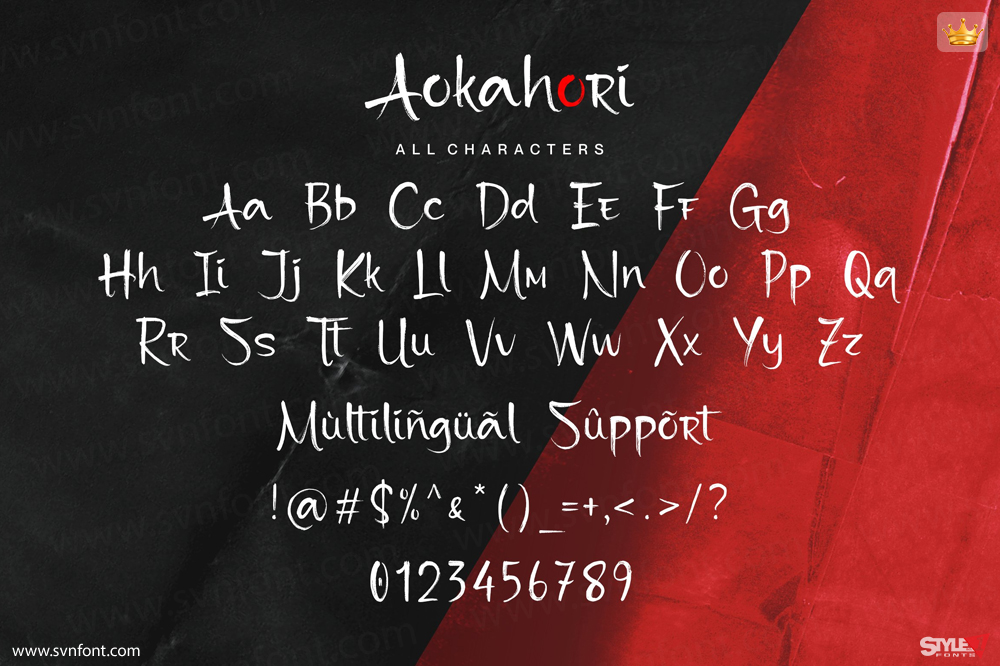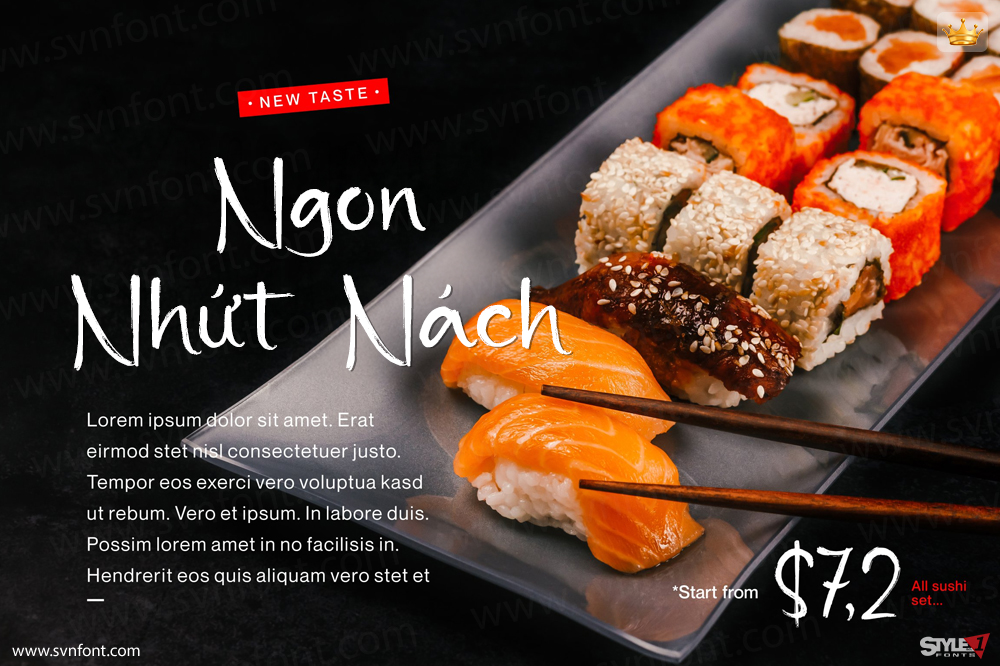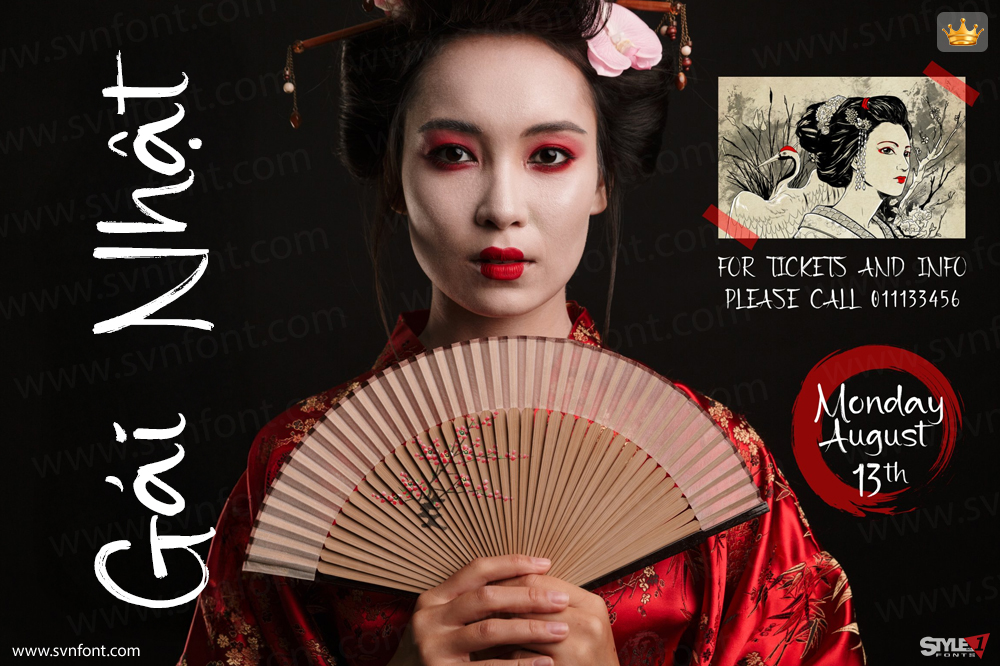
Trân trọng giới thiệu, Aokahori, một phông chữ cọ vẽ phong cách Nhật. Aokahori hoàn hảo cho mọi tiêu đề, logo, bao bì sản phẩm, dự án xây dựng thương hiệu, tạp chí, mạng xã hội, đám cưới hoặc chỉ đơn giản là dùng để thể hiện chữ trên nền. Aokahori cũng hỗ trợ đa ngôn ngữ.
Nhà thiết kế: Fachrizal Yusuf
Nhà phát hành: Allouse Studio